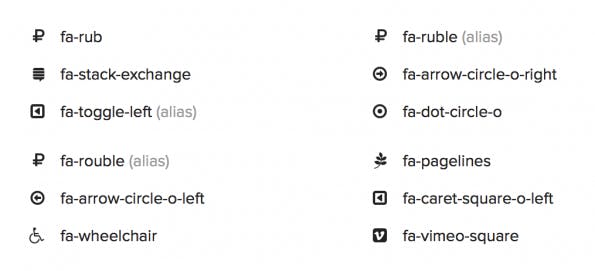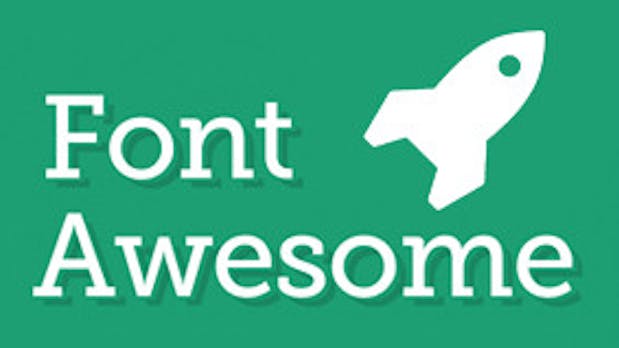
Font Awesome: Das ist neu in Version 4.0 des Icon-Fonts
Font Awesome ist eines der besten Icon-Font-Sets auf dem freien Markt. Mit Font Awesome erhältst du über 370 Icons, die du in deine Webseite einbauen und mit CSS problemlos anpassen kannst. Das Set hat gegenüber klassischen Icons den Vorteil, dass die beinhalteten Icons unendlich und verlustfrei skalierbar sind, mit CSS im Aussehen angepasst werden können und im Vergleich zu bildbasierten Lösungen deutlich weniger Kilobyte auf die Waage bringen.
Font Awesome 4.0 – Das ist neu:
Ein Vorteil, den auch das neue Bootstrap 3 für sich nutzt. Das CSS-Framework aus dem Hause Twitter hat im neuen Release die alten PNG-Glyphicons durch eine neue Icon-Font-Version ersetzt. Auch Font Awesome bietet in der Version 4.0 neben zehn neuen Icons eine vollständige Bootstrap-Kompatibilität und erweitert so das 180 Zeichen starke Glyphicon-Set auf stolze 550 Symbole.
Font Awesome 4.0: Zehn neue Icons. (Screenshot: Font Awesome)
Anders als viele andere Icon-Fonts ist Font Awesome nicht nur gut anzusehen, sondern auch Screen-Reader-kompatibel. Für das neue Release wurde der Icon-Font von Grund auf überarbeitet und für eine bessere Performance optimiert. Neben der Kompatibilität zu Bootstrap wurde auch daran gearbeitet, eine bessere Kompatibilität mit anderen Frameworks – beispielsweise dem Foundation-Framework – zu gewährleisten. Hierfür wurden die Namenskonventionen für den Einsatz der Icons komplett überarbeitet.
Font Awesome im Einsatz
Die Benutzung von Font Awesome geht genauso einfach von der Hand wie die von Bootstrap-Icons. Nachdem du das Font-Awesome-Stylesheet eingebunden hast, kannst du <i>-Tags mit zu den Buttons dazugehörigen Klassen versehen, um so das gewünschte Icon vom Browser darstellen zu lassen.
Mit Hilfsklassen kann die Größe des Icons einfach und ohne separates CSS gesteuert werden. Mit den Klassen fa-lg (+33%), fa-2x, fa-3x, fa-4x oder fa-5x kann die Icon-Größe direkt im HTML gesteuert werden. Außerdem bietet Font Awesome die Möglichkeit, die Ausrichtung der Icons zu ändern oder sie zu spiegeln, mehrere Icons übereinander zu stapeln oder animierte Icons – beispielsweise für einen Ladezustand – einzusetzen.